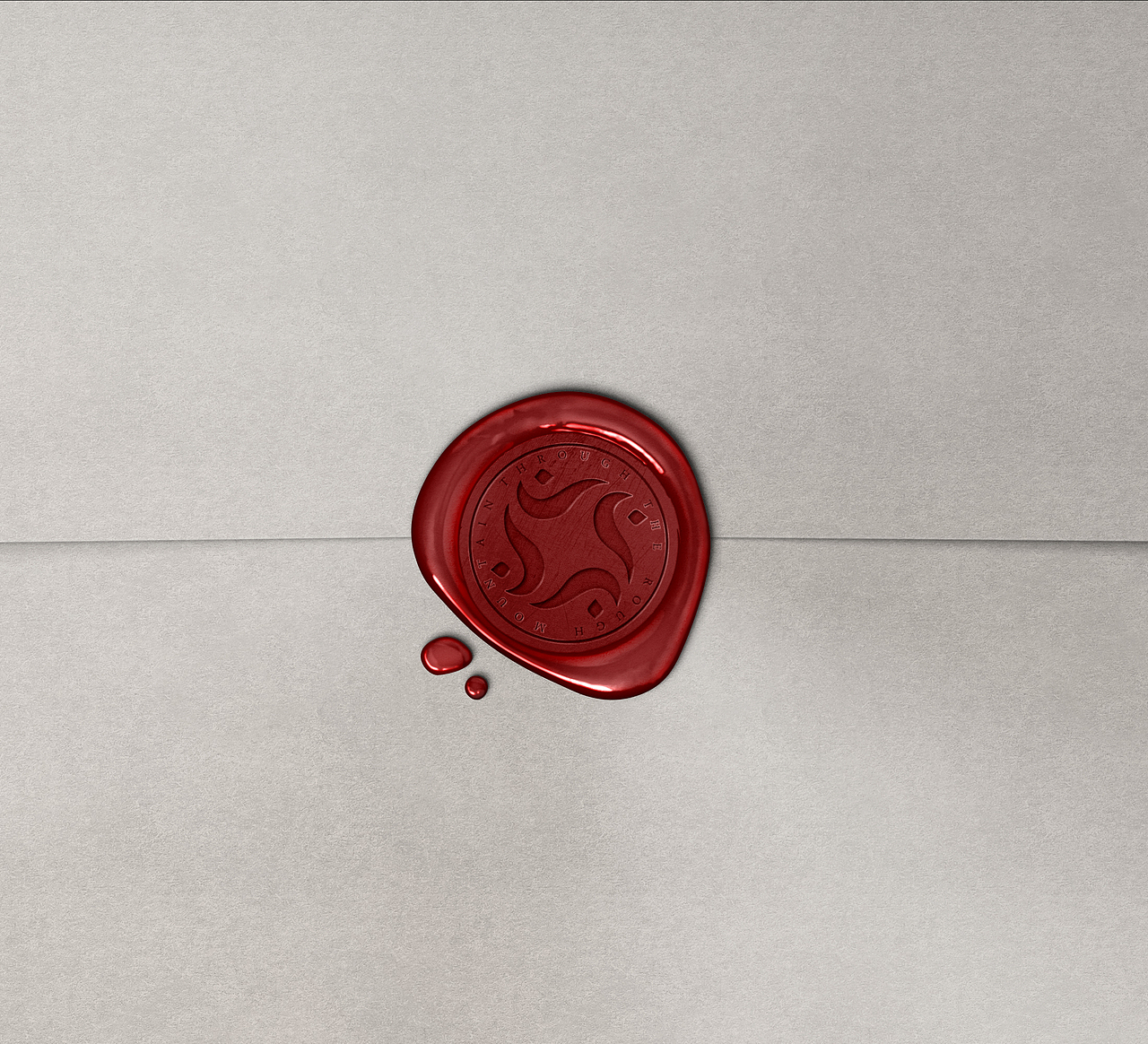
瑞阳不动产——公司年会物料
瑞阳不动产,2017年会,主题一程山路。(原本是绽放,后来因为业绩种种原因改为一程山路)
做了很多版,最终敲了这一稿,个人比较喜欢蓝色调的,女性领导喜欢偏紫色的。
因为较忙,东西比较杂没有整理。所以传了一些看稿。当做是记录吧。
(后面是绽放系列的稿子)
偏蓝稿
偏紫稿
纸巾盒平面图
纸巾盒效果图
甲方爸爸的邀请函
业务员的邀请函
信封
桌号卡
台卡
火漆印章两款
山字体的图形化,一程山路是大家一起共同走过的。
同舟共济贺卡
一个小H5作品邀请函宣传
绽放系列(风格没统一)
入场券